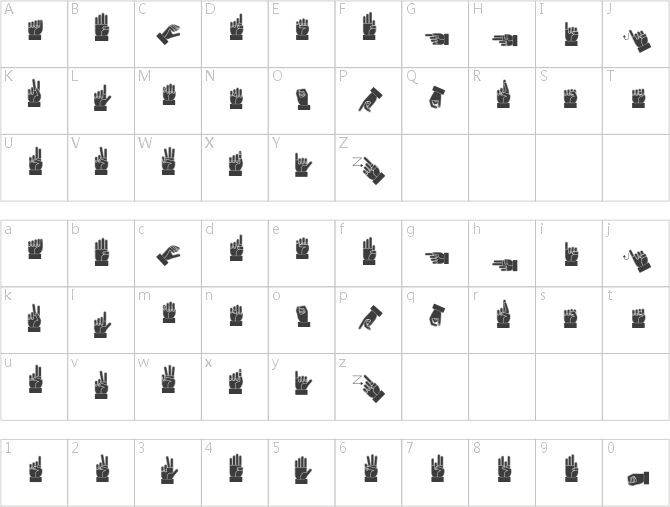
Dissaramas CRU Fingerspelling 詳情頁
Dissaramas CRU Fingerspelling字體字庫是一款讓人賞心悅目、百看不厭的英文字體,適合各類廣告和產(chǎn)品包裝設(shè)計應(yīng)用,字體大小0.15MB,格式為ttf字體,上傳用戶是瓜皮,作者/版權(quán)方為未知